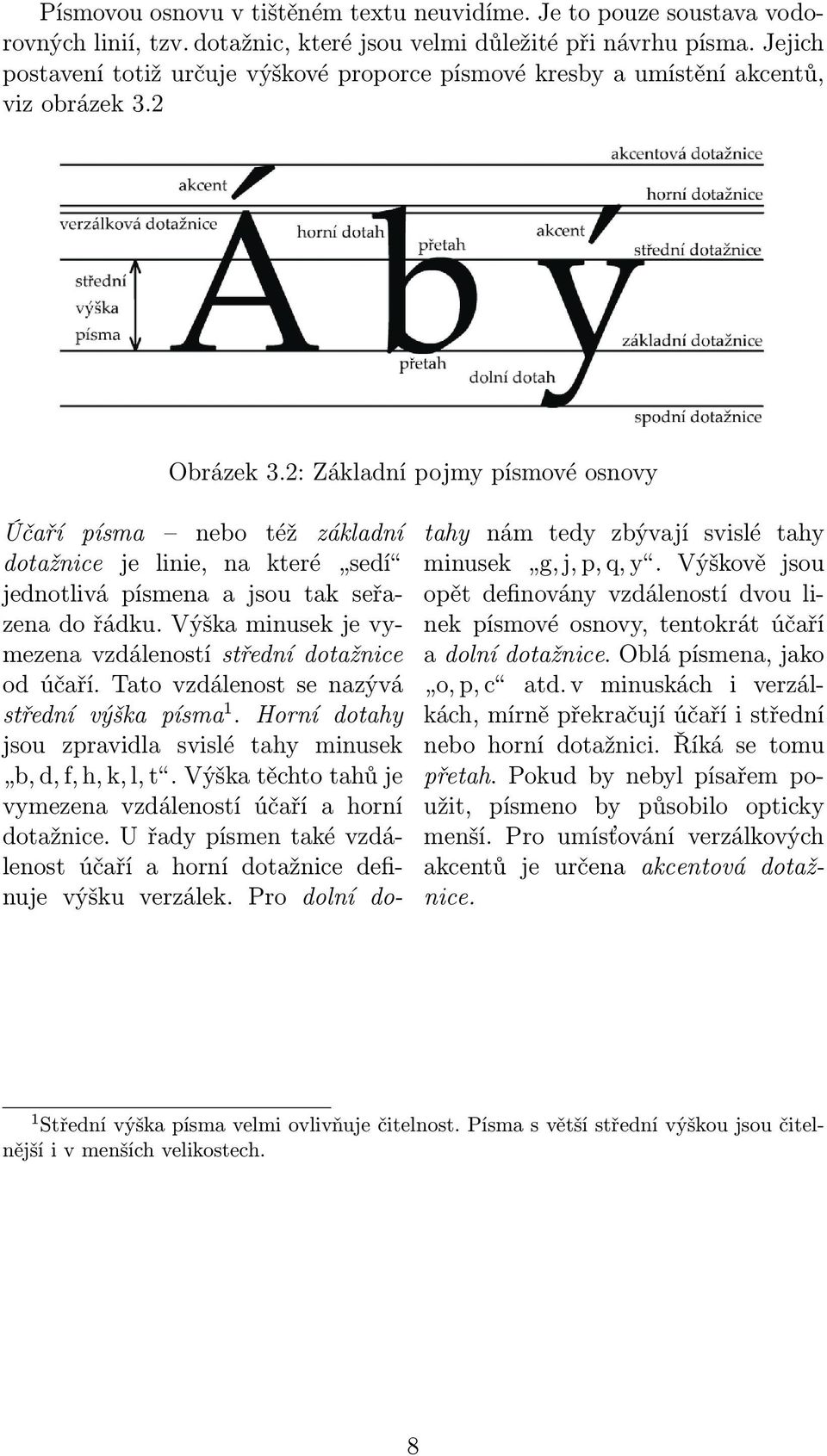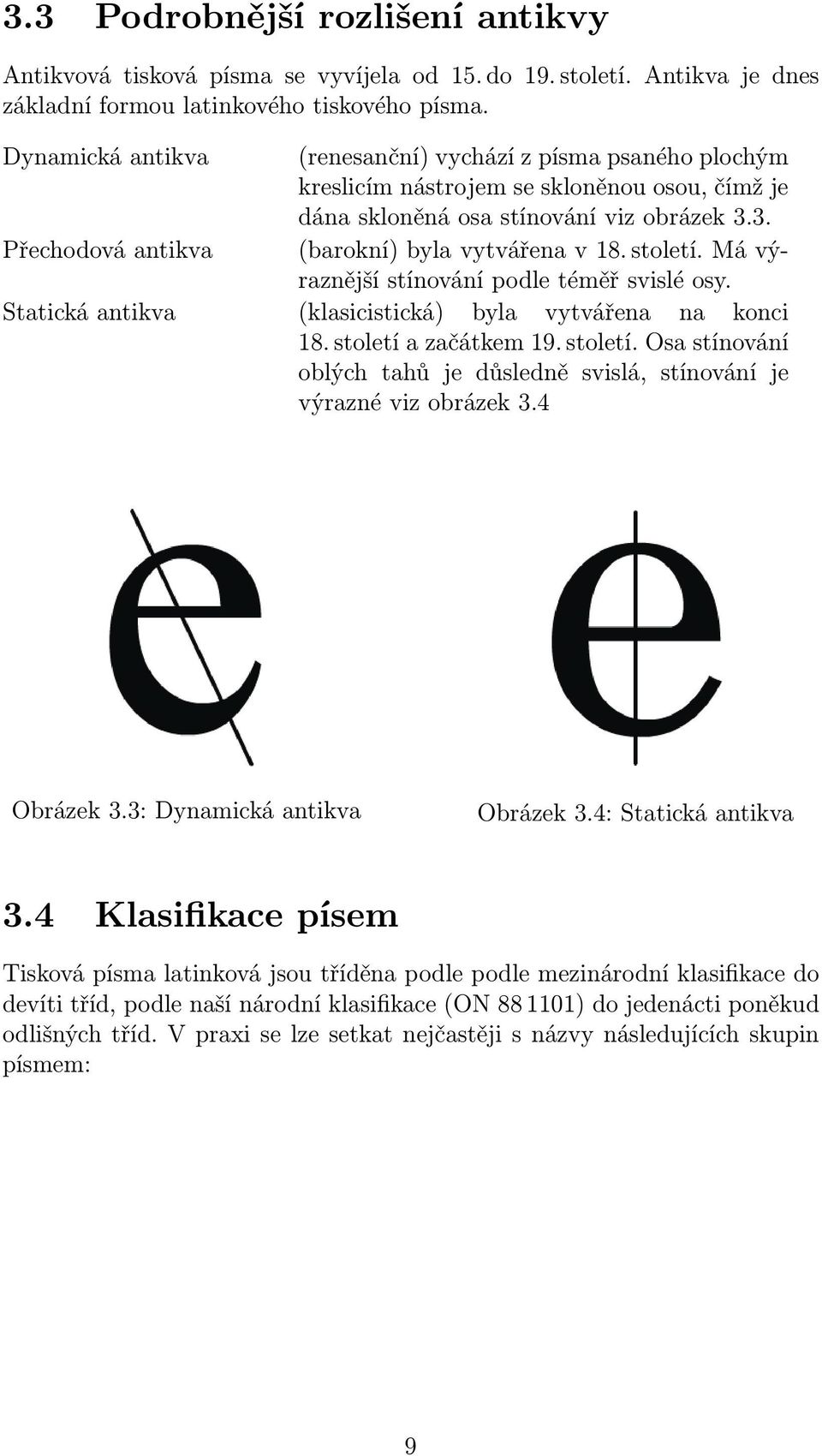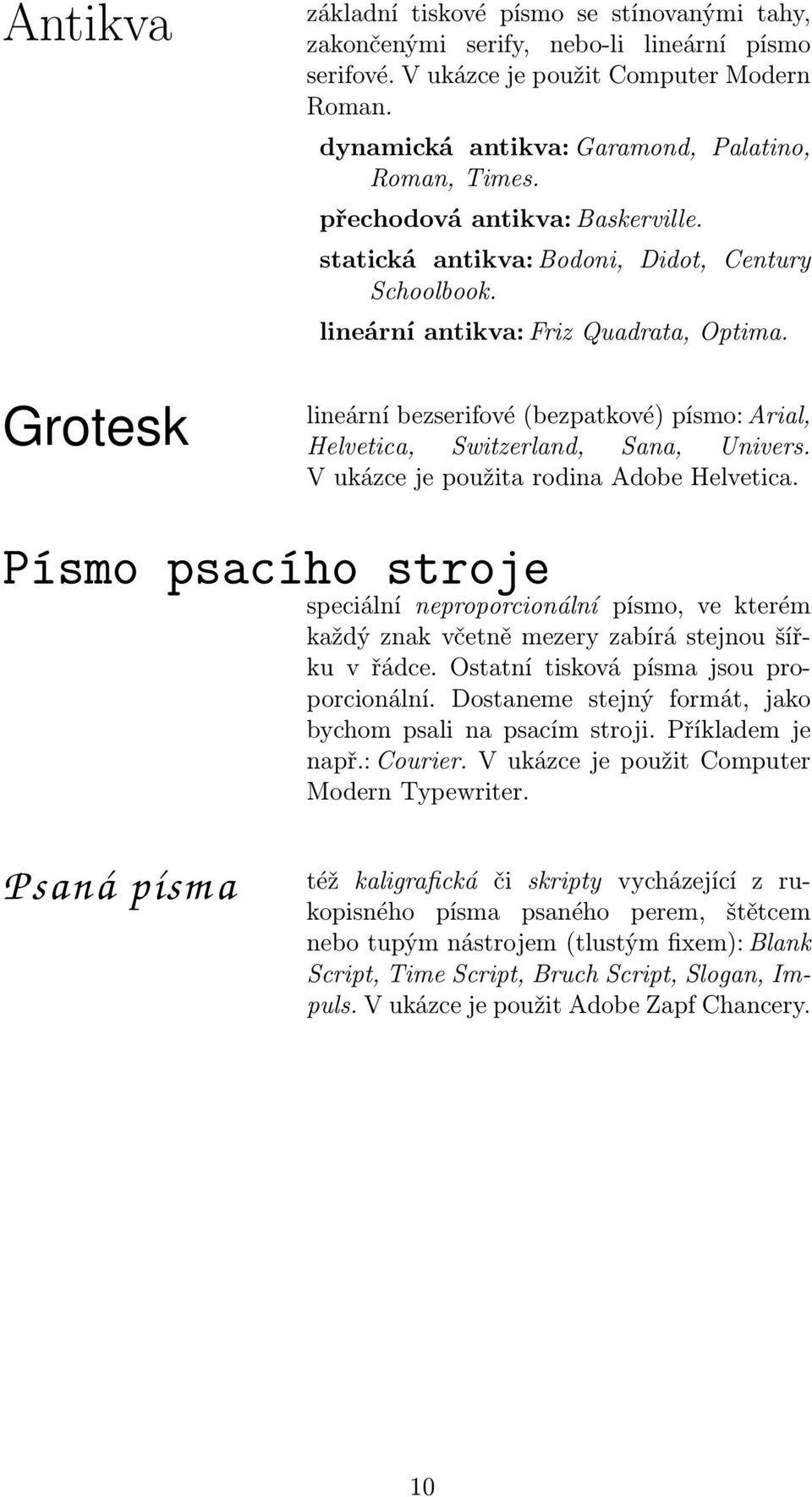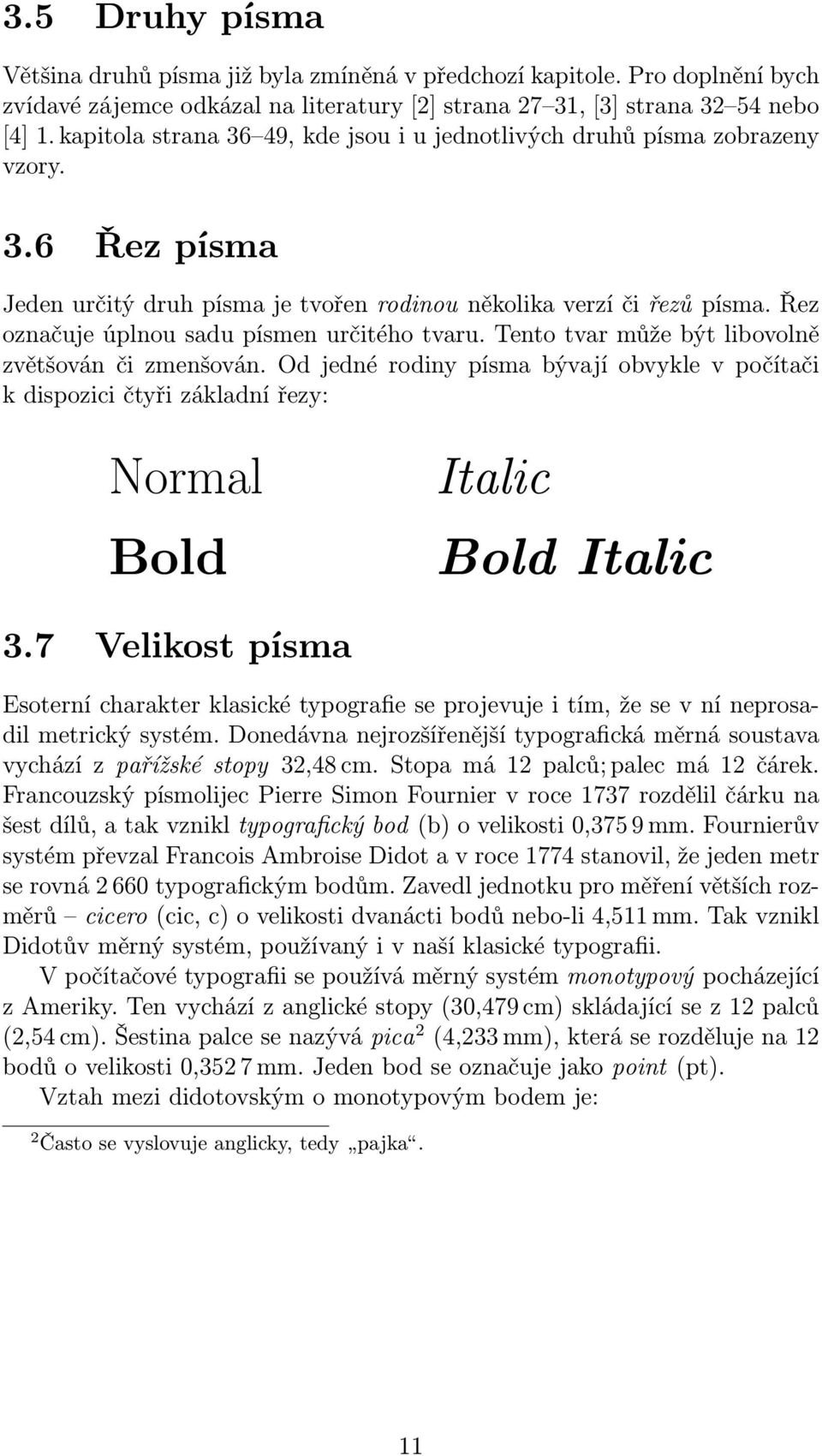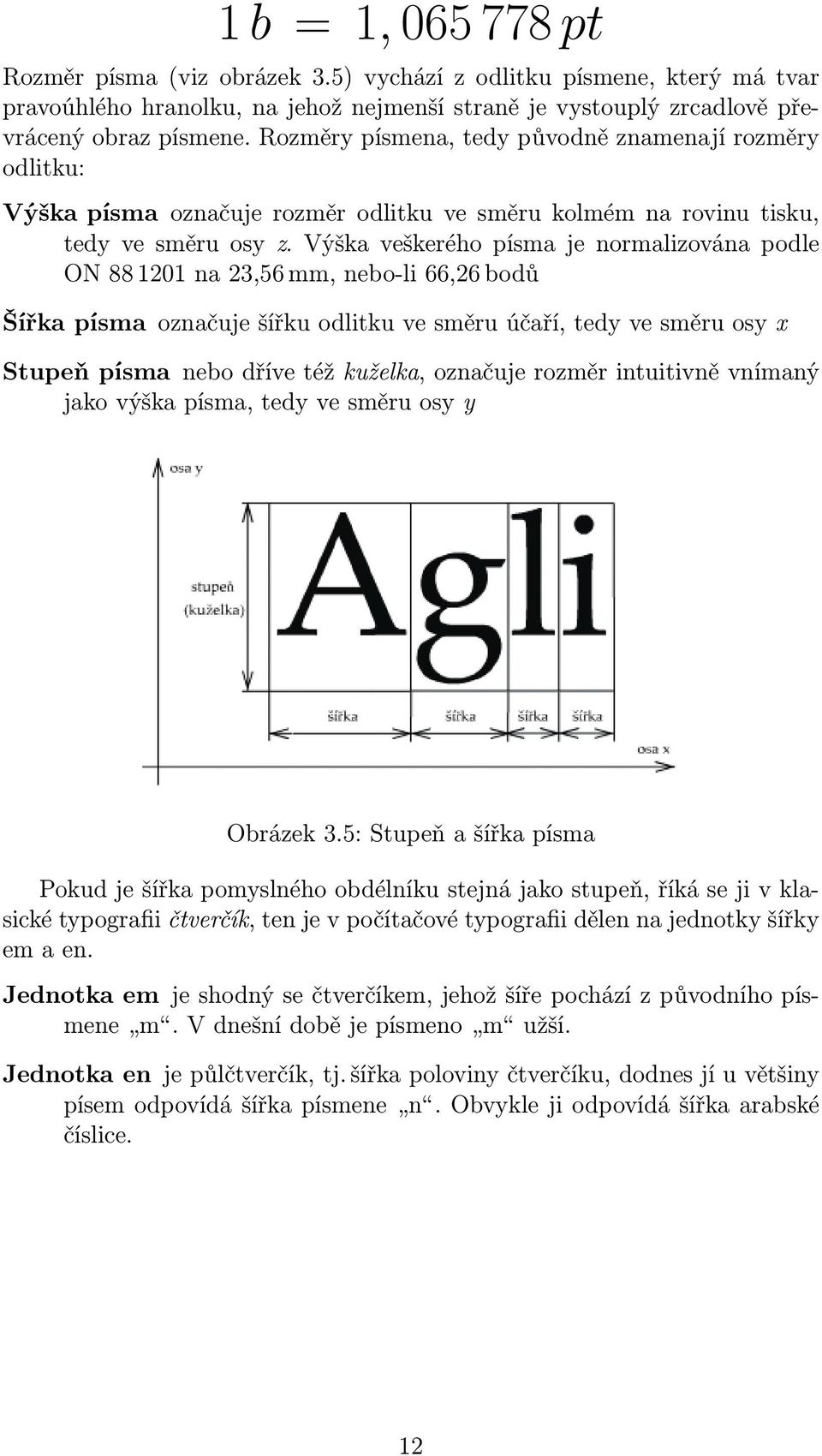
3 Kapitola 1 Úvod 1.1 Historie písma trochu jinak Kdysi v dávnověku, kdy ještě lidé neznali písmo, se veškeré slovesné kulturní dědictví předávalo od úst k uchu. Tehdejší vzdělanci si pamatovali desítky tisíc slok a dokázali je přednášet a předávat dál v nezměněné podobě. Když bylo vynalezeno písmo, používalo se dlouho pouze k praktickým účelům evidence, obchodu a práva. Prastaré pověsti naznačují, že dávnověcí intelektuálové se zaváděním písma do kulturní sféry bránili. Varovali před písmem, jako před nebezpečím, které oslabí lidskou paměť částečně měli pravdu, ale díky písmu sidnesmůžekaždýnapsatipřečíst,cochce. Předpětistyšedesátiletybylvynalezenknihtisk 1 ;původnějakotajné černéumění.podobupětsetletpřipravovalitiskypouzezasvěcenýmistři. Typografie byla donedávna elitním učením, jen pro zasvěcené. Příprava tiskoviny byla velmi nákladnou a složitou záležitostí. Z matric pro tisk se ulívaly jednotlivé litery, ty se sesazovaly v řádky, pak ve strany a nakonec samotný technologicky složitý postup. S vynálezem počítače, laserových tiskáren, textových procesů se neuvěřitelně proces výroby tiskoviny zjednodušil a zdemokratizoval. To má za následek přerušování i elementárních typografických pravidel nejen v tiskové produkci počítačových firem, ale i v krásné literatuře vydávané u mnoha nezávislých nakladatelství. Na druhou stranu si dnes může připravit technicky dokonalou tiskovinu každý. 1 Knihtiskvynalezlokoloroku1450mohučskýzlatníkJohannesGensfleischGutenbegr. 1
4 1.2 Vznik českého písma Písmo je tak staré jako písemnictví. Je grafickým obrazem jazyka. Čeština právě tak jako jiné národní jazyky evropské nebyla jazykem spisovným, nýbrž hovorovým. Nejstarší památky českého písemnictví z doby románské nebyly psány češtinou, ale latinou nebo staroslovenštinou, tedy jazykem církevním, poněvadž to byly knihy bohoslužebné, legendy a kroniky, určené jen pro slabou vrstvu vzdělanců z církevních škol a klášterů. Teprve koncem 14. století TómazeŠtítnéhopovýšilsvůjmateřskýjazykzaspisovnýastávásetak zakladatelem národního písemnictví. Čtenáře zajímající se o vznik českého písemnictví a tvorby písma odkazuji na literaturu[5]. 1.3 Co je typografie Slovo typografie je složeno ze základu typus a gráfo. Latinské typus (znak, vzor) pochází z řeckého typus(tep, ráz, etymologická příbuznost s naším slovem tep, tepat). Řecké gráfo znamená píši. Doslovně tedy typografie znamená psaní znaků. Po vynálezu knihtisku se pojmem typografie označoval veškerý knihtisk, tzn. typografem byl často označován nakladatel, redaktor, korektor, sazeč, tiskař a vazač v jedné osobě. Dnes je za typografa považován odborný pracovník,ovládajícíestetickouúpravusazby.dnešnítypografickápravidla navazují na pravidla pravopisná a patří ke kulturnímu dědictví. Typografická pravidla nejsou intuitivně samozřejmá. Často si zdánlivě odporují. Míra důležitosti jejich dodržování je krajně subjektivní. Aspekt estetického působení tiskoviny není založen pouze na citu pro krásno, ale také na citupronoblesu.tiskovinareprezentuje,podobnějakooblečení.zatímco společenskou důležitost noblesního oblečení dnes už chápe i začínající podnikatel, důležitost noblesních tiskovin občas nechápou ani velké firmy. Přitom prospekt, porušující základní typografická pravidla, působí ve společnosti asi podobně, jako špinavé džíny na společenském večírku. Typografie patří do esoterních nauk, tj. nauk jen pro zasvěcené. 2
5 Kapitola 2 Vývoj písma 2.1 Prehistorie písma Historickými předchůdci písma byly piktogramy a ideogramy. Piktogramy Ideogramy znázorňují sdělení obrazově, podoba a čtení nejsou pevně stanovena. Neváží se na konkrétní jazyk, tj.jejich smysl je zřejmý i bez znalosti jazyka. V dnešní době jsou stále užívány, jako je například značka pro zákaz kouření apod. znázorňují sdělení symbolem, který je vázaný na určitý jazyk. Příkladem mohou být uzlové značky Inků a Aztéků. 2.2 Počátky historie písma Nejstarší písmo je obrázkové jeden obraz vyjadřuje jeden pojem. Další vývojová stádia představují slovní, slabičná a hlásková(abecední) písma. Dodnes běžně používáme některé slovní symboly, nazývané též logogramy, tím je například,%,&,$. Klínové písmo Babylóňanů a Asyřanů vzniklo před více než pěti tisíci lety. Zapisovalo se dřevěnými rydly do hliněných destiček, které se vypalovaly.psaloačetlosezzlevadoprava. 3
6 Egyptské písmo se vyvíjelo z původních obrázkových slovních hieroglyfů až k písmu hláskovému. V dlouhé historii Egypta se postupně vytvořily tři písmenové soustavy: Hieroglyfy (písmo posvátných rytin) byly vynalezeny před pěti tisíci lety jako obrázkové slovní písmo tvořené asi znaky. Rozluštěny díky J.F.Champollionoviažvroce1822. Hieratické písmo(kněžské) vzniklo zjednodušením hieroglyfů na soubor asi 600 znaků.rytodokameneipsánonapapyrus. Čínské písmo Fénické písmo Démotické písmo(lidové) už mělo pouze 24 znaků pro souhlásky. Samohlásky bylo nutno při čtení doplňovat podle textu. Psalo se na papyrus. vzniklo zcela nezávisle před čtyřmi tisíci lety adodnesseudrželojakopísmoslovní.mávíce než znaků. Pro běžnou potřebu vystačí 3000znaků.Píšeseshoradolůazprava doleva, od roku 1956 i zleva doprava. Japonci a Korejci toto písmo převzali a zjednodušili je ve slabikové. Číně patří dík za vynález papíru roku 105 našeho letopočtu. Vynalezl jej Číňan Čchaj Luan. vzniklo před více než třemi tisíci lety na území dnešního Libanonu a Sýrie. Bylo tvořeno sadou 22 souhláskových písmem a psalo se zprava doleva. Je prokazatelně historickým prapředkem naší latinky. 4
7 2.3 Řecké písmo Řekové přijali fénické písmo asi v 10. století před naším letopočtem. Některé znaky přetvořili na samohlásky a některé znaky vypustili. Začali též měnit směr písma. Postupně vzniklo obousměrné písmo zvané bustroféda první řádka zprava doleva, druhá zleva doprava, třetí zprava doleva atd. Později se ustálilsměrpísmazlevadoprava,užívanédodnesvceléevropě.vtédobě ještě neměli Řekové jednotný jazyk, a tak vznikly dvě skupiny východní a západní řecká abeceda Východní větev azbuka Z východních písmen se vyvinulo dnešní řecké písmo a písma slovanská hlaholice, kyrilice a azbuka. Hlaholice Kyrilice Azbuka byla nejstarším slovanským písmem. Vytvořil ji soluňský učenec Konstantin zvaný Cyril, kterýpřišelvroce863sesvýmbratremmetodějem do Velkomoravské říše šířit křesťanství a byzantskou vzdělanost. Hlaholice měla 43znakůačetlaseprýobtížně.VČecháchse udržela jen do 12. století. vznikla na území Bulharska po příchodu Metodějových žáků, kteří tam přišli po rozpadu Velkomoravské říše. Podobala se více řeckému písmu a učila se snadněji než hlaholice. Šířila sedosrbska,ruskaanaukrajinu. vznikla dalším vývojem kyrilice na území RuskaaUkrajiny.Vroce1708jinechalPetrVeliký zjednodušit na takzvanou občanskou abecedu graždanku. Ta se používá prakticky dodnes Západní větev latinka Asi 300 let před naším letopočtem převzali řecké písmo Italikové na Apeninském poloostrově. Spolu s historií Říma probíhal historický vývoj latinky našeho nynějšího písma. 5
8 2.4 České písmo PopáduVelkomoravskéříševroce907začalnanašeúzemípronikatvliv katolické církve ze západu. Latina se stala liturgickou i úřední řečí a latinka na našem území postupně bezezbytku vytlačila hlaholici. Pro zápis literatury ve slovanském jazyce bylo nutno latinku upravit. Důležitou změnu pravopisu navrhlvroce1414janhusvesvémlatinskypsanémdíledeortographia bohemica. 6
9 Kapitola 3 Vlastnosti písma 3.1 Názvosloví Nejprve, než-li se plně začneme věnovat samotné typografii, připomenu několik výrazů použitých v dokumentu, aby čtenář neztratil nit v plynulosti pochopení textu. Při psaní se běžně setkáváme s pojmem velká a malá písmena abecedy, nebo také hůlkové písmo. V typografickém názvosloví je správný výraz pro velká písmena verzálky(majuskule) a pro malá písmena minusky (minuskule). 3.2 Písmová osnova a kresba Kresbapísmovýchznakůseprovádívpísmovéosnově.Kresbapísmena F je zobrazena na obrázku 3.1. serif (patka) Fvedlejší tah hlavní tah (døík) serif (patka) vedlejší tah nábìh serif (patka) Tahpísma jekresebnýtahznaku,apodletvaruse rozlišuje na oblý, přímý a stínovaný tah. Stínování je zesilování částí nebo celých tahů, zvláště u oblouků a dříků. Tloušťka(duktus) tahu závisí na směru tahu. Lineární písmo není stínované, tj. všechny jeho tahy mají stejný duktus. Serif(patka) je příčné zakončení tahu písma, u většiny písmem předchází náběh. Obrázek 3.1: Názvy částí kresby znaku písma 7
10 Písmovou osnovu v tištěném textu neuvidíme. Je to pouze soustava vodorovných linií, tzv. dotažnic, které jsou velmi důležité při návrhu písma. Jejich postavení totiž určuje výškové proporce písmové kresby a umístění akcentů, viz obrázek 3.2 Obrázek 3.2: Základní pojmy písmové osnovy Účaří písma nebo též základní dotažnice je linie, na které sedí jednotlivá písmena a jsou tak seřazenadořádku.výškaminusekjevymezena vzdáleností střední dotažnice od účaří. Tato vzdálenost se nazývá střední výška písma 1. Horní dotahy jsou zpravidla svislé tahy minusek b,d,f,h,k,l,t.výškatěchtotahůje vymezena vzdáleností účaří a horní dotažnice. U řady písmen také vzdálenost účaří a horní dotažnice definuje výšku verzálek. Pro dolní dotahy nám tedy zbývají svislé tahy minusek g,j,p,q,y. Výškově jsou opět definovány vzdáleností dvou linek písmové osnovy, tentokrát účaří a dolní dotažnice. Oblá písmena, jako o,p,c atd.v minuskách i verzálkách, mírně překračují účaří i střední nebo horní dotažnici. Říká se tomu přetah. Pokud by nebyl písařem použit, písmeno by působilo opticky menší. Pro umísťování verzálkových akcentů je určena akcentová dotažnice. 1 Střednívýškapísmavelmiovlivňuječitelnost.Písmasvětšístřednívýškoujsoučitelnější i v menších velikostech. 8
11 3.3 Podrobnější rozlišení antikvy Antikvová tisková písma se vyvíjela od 15. do 19. století. Antikva je dnes základní formou latinkového tiskového písma. Dynamická antikva Přechodová antikva Statická antikva (renesanční) vychází z písma psaného plochým kreslicím nástrojem se skloněnou osou, čímž je dána skloněná osa stínování viz obrázek 3.3. (barokní) byla vytvářena v 18. století. Má výraznější stínování podle téměř svislé osy. (klasicistická) byla vytvářena na konci 18. století a začátkem 19. století. Osa stínování oblých tahů je důsledně svislá, stínování je výrazné viz obrázek 3.4 Obrázek 3.3: Dynamická antikva Obrázek 3.4: Statická antikva 3.4 Klasifikace písem Tisková písma latinková jsou tříděna podle podle mezinárodní klasifikace do devíti tříd, podle naší národní klasifikace(on ) do jedenácti poněkud odlišných tříd. V praxi se lze setkat nejčastěji s názvy následujících skupin písmem: 9